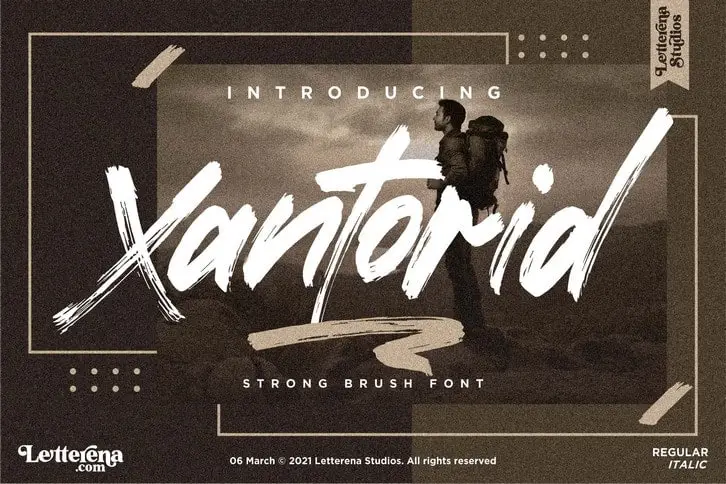
Xantorid Brush Font – Download Grátis
Xantorid Brush Font é uma tipografia de exibição casual e cuidadosa, com uma textura grossa que ganha vida graças ao uso de uma caneta-pen. Esta fonte é perfeita para qualquer projeto, desde logomarcas e projetos de marca até designs de mobília, embalagens de produtos, têxteis, postais e cartões de boas-vindas. Perfeito tanto para trabalhos profissionais quanto para criações artesanais, este tipo de letra oferece um toque sofisticado e autêntico que certamente encaixará perfeitamente em sua próxima peça de design. Seja qual seja o seu projeto, Xantorid Brush Font tem a capacidade única de dar uma sensação única de elegância e personalização.